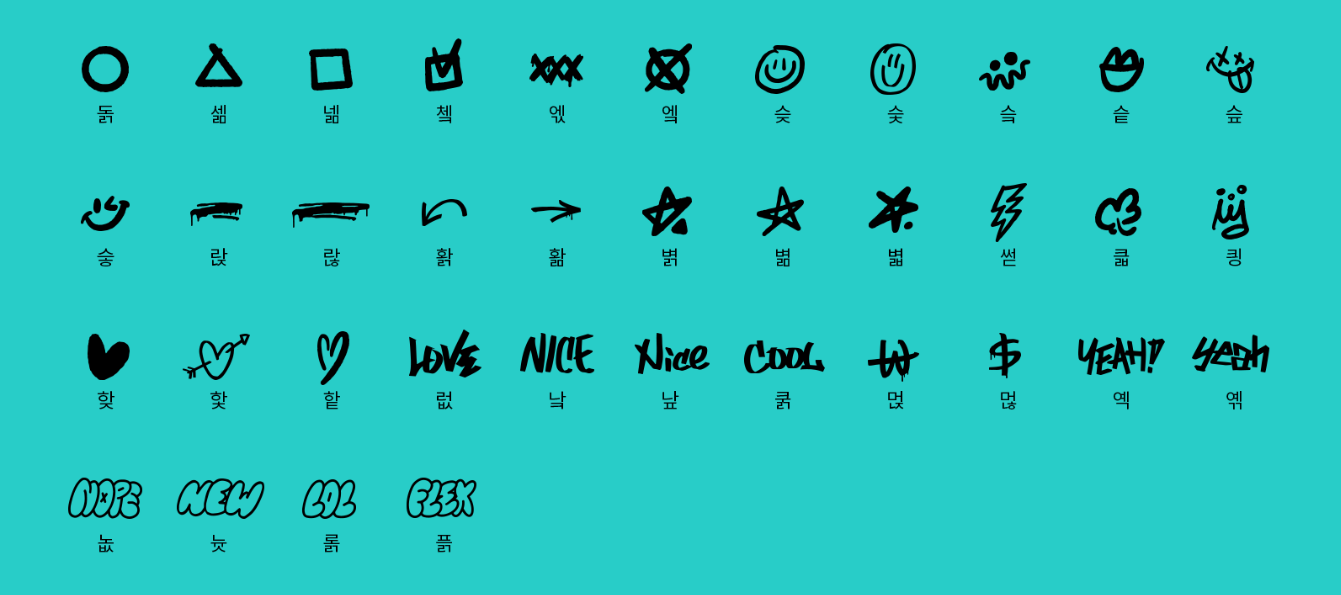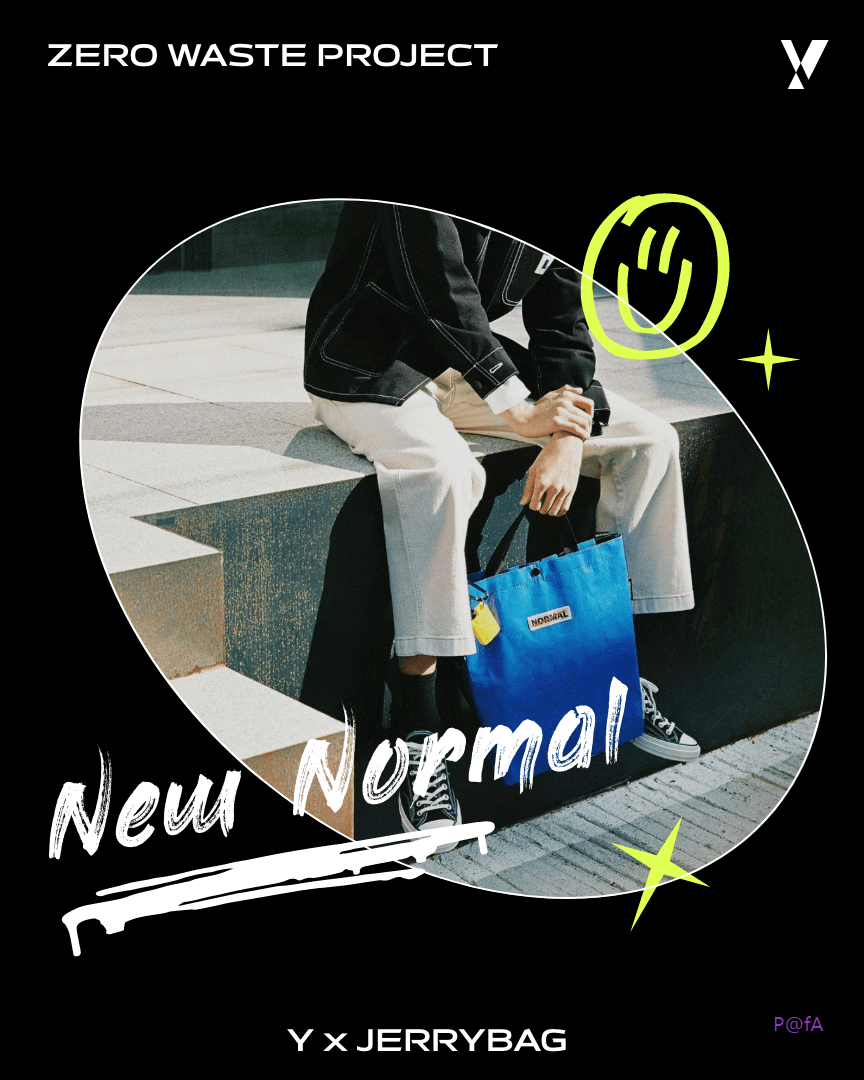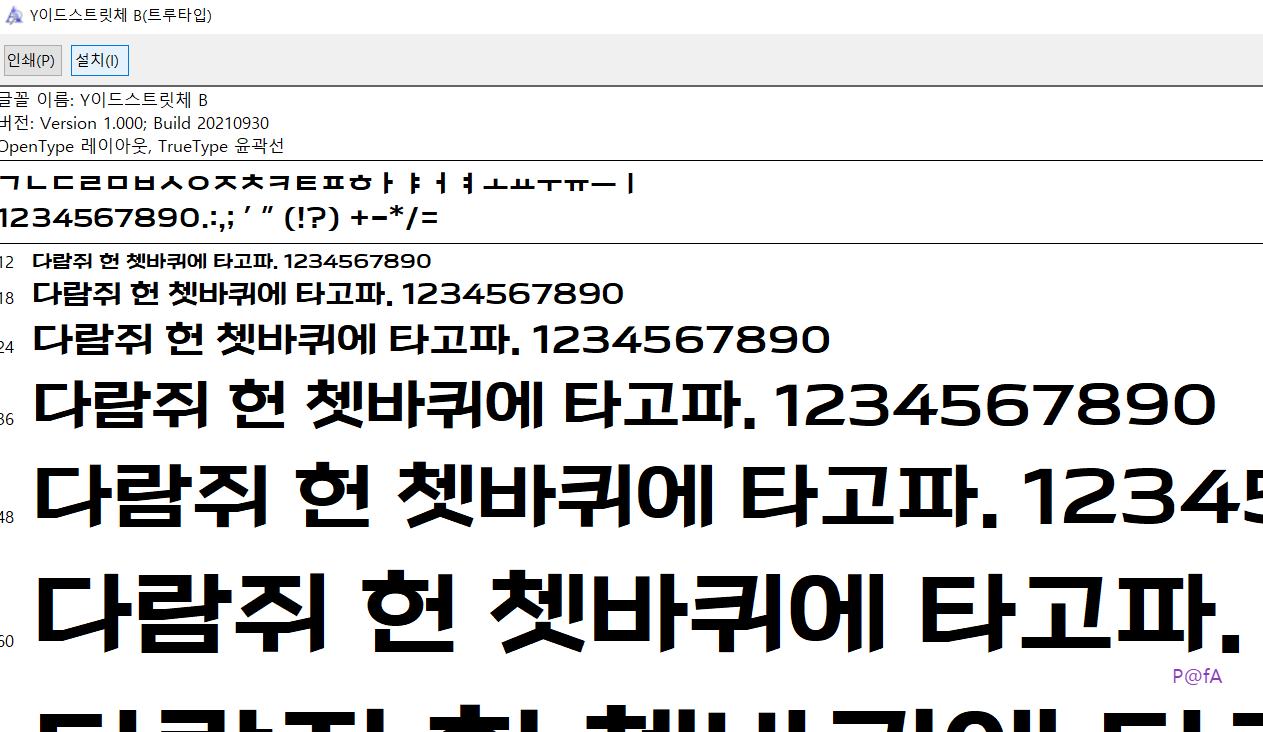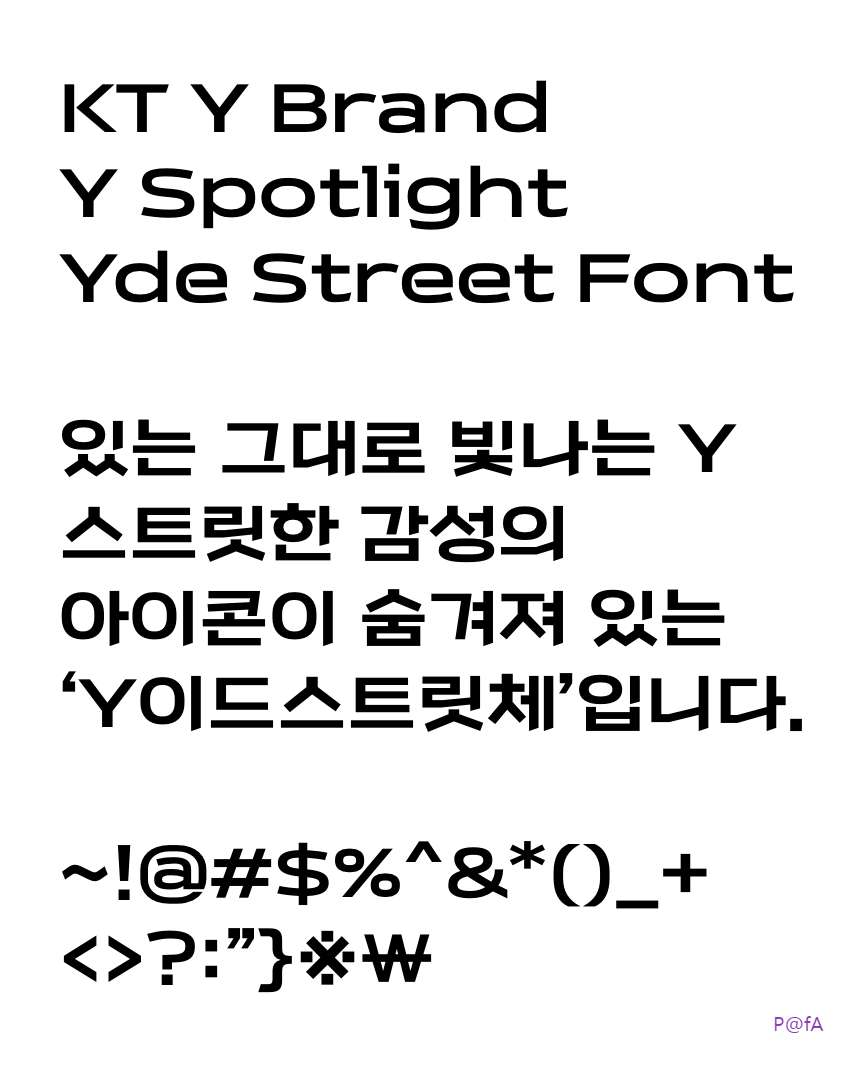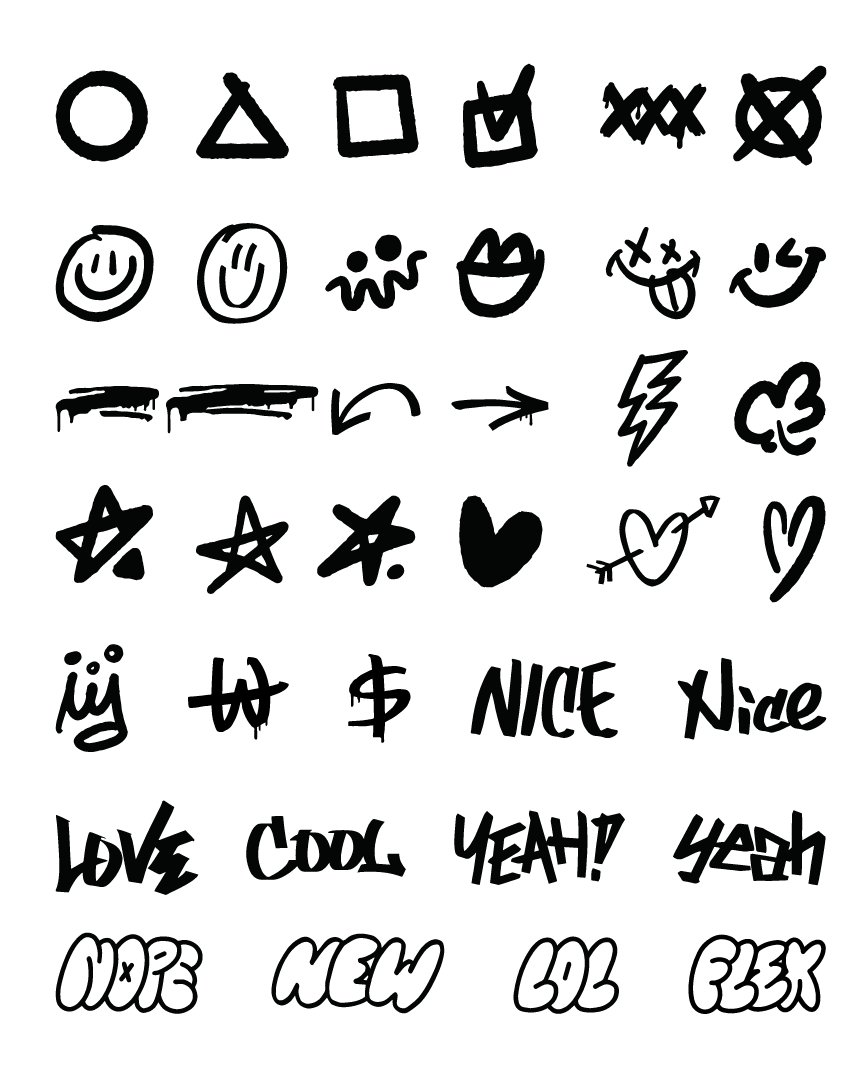
KT에서 젊은 세대의 취향에 맞는 무료 폰트로 배포한 Y이드스트릿체를 무료로 다운로드하는 방법을 살펴본다. 더불어 누구나 무료로 사용이 가능한 Y이드스트릿체를 컴퓨터에 설치하는 방법과 코딩 시에 사용하는 방법도 살펴본다.
누구나 개인적인 용도뿐만 아니라 상업적인 용도 즉, 영리 또는 비영리 목적으로도 무료로 사용할 수 있도록 제공하는 무료 폰트인 Y이드스트릿체를 소개한다. 해당 Y이드스트릿체는 KT 공식 대학생 마케팅 서포터즈인 Y퓨처리스트와 함께 MZ세대의 아이디어를 담아 제작된 글꼴로 캐주얼하고 미니멀한 가치를 담은 스테이셔너리한 고딕 형태의 글자에 스트릿한 그래피티 감성의 아이콘까지 있는 그야말로 엣지와 트렌디함을 모두 담고 있는 글꼴이다. 다음에서 Y이드스트릿체를 무료로 다운로드해서 컴퓨터에 설치하는 방법을 비롯해서 다양한 용도로 사용하는 자세한 방법을 확인할 수 있다.
KT에서 20대를 타깃으로 만든 브랜드인 Y를 담고 있는 KT Y 공식홈페이지에서 2021년에 한글날을 기념하여 제작한 Y이드스트릿체를 누구나 사용 가능한 무료 폰트로 배포하고 있다.
Y이드스트릿체는 아래의 이미지에서 보듯이 전체적으로 직선과 사선의 조화가 도드라지는데 이를 기반으로 대칭되는 형태로 글자의 안정감을 형성하고 있다.
더불어 와이드하고 스트릿한 감성의 이모지 37종도 제공하는데, 해당 이모지 즉, 손으로 직접 그린 듯한 귀여운 37종의 아이콘은 잘 사용하지 않는 한글 낱자에 아이콘을 배치하고 있어서 숨은 아이콘을 찾는 재미도 있다.